השאלון עם ליאת לזבר
הכירו את ליאת לזבר, בת 25, סטודנטית שנה ג׳ לעיצוב באוניברסיטת חיפה. היא נולדה בשנת 2000, גדלה בנצרת־עילית וכיום חיה בחיפה – שלדבריה היא "העיר הטובה בעולם". בעולם העיצוב ליאת נמשכת במיוחד למיתוג, טיפוגרפיה, איור ועבודות קראפט, ומעריכה מעל הכול את החופש שהמקצוע מעניק לה: “האפשרות לביטוי אותנטי של כל מה שמתחולל בנפש”. מחוץ לסטודיו, אפשר למצוא אותה בהופעה חיה, ברכישת כרטיסים להופעה הבאה, או משוטטת בין במות בפסטיבל מוזיקה.
היי ליאת, מה שלומך? איפה אנחנו תופסים אותך השבוע?
היי! השבוע הוא שבוע שגרתי, כרגע בחדר שלי בונה פלייליסט חדש בספוטיפיי ותוהה אם חם מספיק לקפוץ לים 🙂
את מעדיפה לעבוד לבד או בצוות?
בשלב הביצוע אני נהנית לעבוד לבד, אבל כשזה מגיע לבריינסטורמינג – לגמרי בצוות!
מה גורם לך להתרגש ולרצות לעצב וליצור?
מה שמניע אותי לעצב וליצור הוא צורך – אישי או כזה שנולד מתוך תגובה למה שקורה בעולם. זו תחושה שבוערת מבפנים, שמאלצת אותי לקום ולפגוש את הדף, החומר או המסך.
מה את עושה כשאין לך מוזה?
חוסר המוזה שלי בעיקר מגיע כשאני מתעסקת בדברים שאני לא באמת אוהבת או ״כי צריך״ לעשות אותם, אז אני מאוד מהר עושה ריסטרט ומדייקת את ההתעסקות כך שאני באמת אתחבר אליה 🙂 וכמובן ששנ״צ.
ומה את עושה בשביל הכיף?
שרה במקלחת, משוטטת בשוק הפשפשים, מבקרת בחנות קריסטלים, מוסיפה דיסק חדש לאוסף שלי – ובעיקר דואגת לפנות זמן לעצמי.
יש לך הרגל מגונה?
לצעוק :״יא! כלב!״ על כל כלב שאני רואה ברחוב 🙂
על איזה פרויקט מעניין עבדת לאחרונה?
לאחרונה חידשתי פרויקט מהשנה הראשונה ללימודים – "חיפה 2083". מדובר בסדרה של גלויות ממקומות אייקוניים בעיר, כפי שהם עלולים להיראות בשנת 2083 אם לא נטפל בזיהום החמור שפוגע בה. כבר אז, בתחילת שנה א׳, הבינה המלאכותית החלה לחלחל אל חיינו, ואזרתי אומץ לנסות לשלב אותה בעבודה. עכשיו, שנתיים אחרי, חזרתי אל הפרויקט כדי לחדד ולדייק אותו, בהשראת ההתקדמות המסחררת שהתחום עבר מאז.
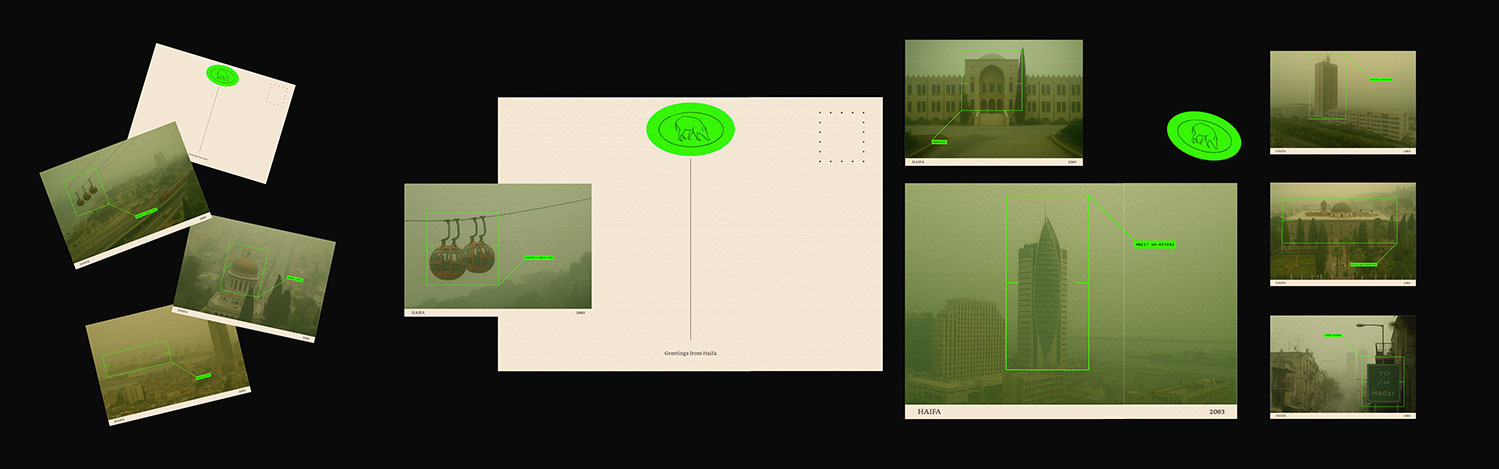
בפרויקט Haifa 2083 מציגה ליאת לזבר סדרת גלויות תיירותיות־אזהרתיות, המדמיינות את חיפה בשנת 2083 תחת ענן זיהום כבד. הדימויים, המבוססים על אתרים אייקוניים בעיר, מעניקים לפורמט הנוסטלגי של הגלויות פרשנות ביקורתית. זהו עיבוד מחודש לפרויקט משנה א׳, שנוצר בקורס "תפיסה חזותית" בהנחיית נסטיה פייביש, וכעת שודרג לאור ההתקדמות בבינה המלאכותית ותחושת הדחיפות סביב משבר האקלים. "כרגע, כתושבת חדשה של חיפה, רציתי לעורר שאלות על אחריות סביבתית והדחקה קולקטיבית," היא אומרת.
מה משך אותך לתחום?
מה שמשך אותי לתחום הוא קודם כול סקרנות. עד לפני ארבע שנים בכלל לא הכרתי את המונח "תקשורת חזותית", אבל כילדה ונערה כל עולמי היה יצירה – עיצוב, ציור, פיסול וכל עבודת קראפט אפשרית. בגיל 16 החלטתי שארצה לעסוק בעיצוב גרפי, אבל כששיתפתי את הרעיון עם המשפחה הסובייטית שלי (אמא, אני אוהבת אותך!), ההתלהבות לא הייתה בשיאה – אז הלכתי ללמוד ביולוגיה, כימיה ומדעי החברה.
בגיל 21 עברתי לתל־אביב, כמו הרבה נערות פריפריה, ושם נחשפתי לראשונה לעולם התקשורת החזותית. חזרתי הביתה עם ההבנה שזה מה שאני רוצה ללמוד, ולהפתעתי אמא שלי אמרה: "כל מה שתרצי – העיקר שתעשי כבר תואר". עם האמירה הזו, הרבה סקרנות וקצת ידע בתחום, ניגשתי למבחני הקבלה לוויצו – והשאר היסטוריה.
תני לנו ציטוט שיעורר בנו השראה.
״כשאת מקבלת את התשובה מתוכך, אף אחד לא יכול לבלבל אותך, את שם.״
לאן ניסית להתקבל ללימודים ולאן התקבלת?
בתקופה שבה ניסיתי להתקבל ללימודים גרתי בתל־אביב, אבל העיר הייתה עבורי כאוטית מדי. הגעגוע לצפון הלך והתחזק, עד שהפך לשיקול המרכזי בבחירה – ולכן ניגשתי למבחני קבלה רק בויצו. לשמחתי, הגעגוע ניצח.
איזה מרצה השפיע/ה עליך במיוחד?
נסטיה פייביש. הראשונה שהצליחה לגרום לי להרגיש שיש ערך למה שאני יוצרת. מלבד היותה מרצה מבריקה וחריפה, היא מעצבת גרפית וחוקרת חזותית ישראלית פוסט־סובייטית עם פרויקט מדהים בשם ״המהגרת״ שנוגע בנבכי הנפש שלי.
איזה מעצב/ת השפיע/ה עליך יותר מכל?
דן רייזינגר. יש באמת צורך להרחיב למה?
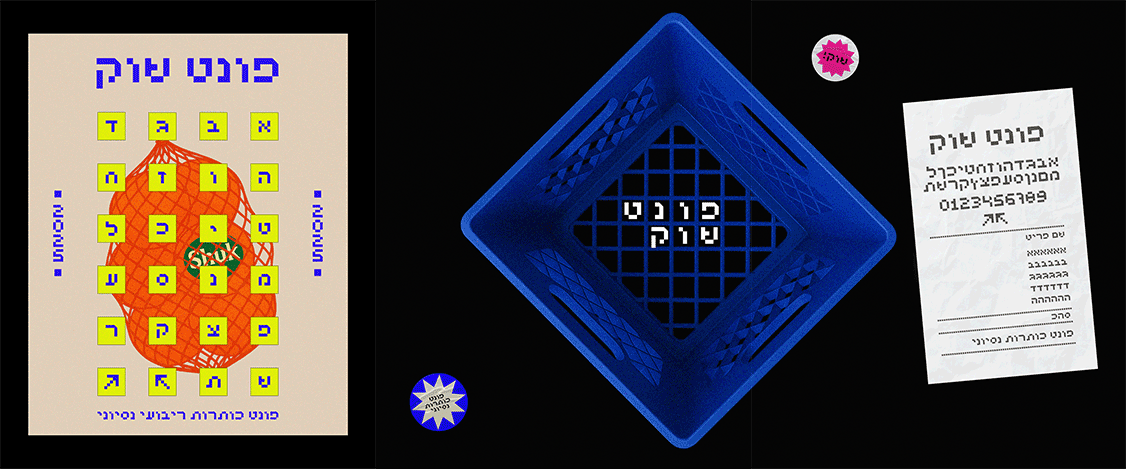
פונט שוק הוא פונט כותרות ריבועי־ניסיוני שיצרה ליאת לזבר במסגרת קורס מיתוג לתערוכת הבוגרים של המחלקה לתקשורת חזותית, 2025. נקודת המוצא שלה הייתה חיפוש אחר מקומות חיפאיים על־זמניים עם אופי מקומי מובהק, וההשראה המרכזית הגיעה משוק תלפיות האגדי – מרחב חזותי יומיומי, לא "מעוצב כמו שצריך", אך שופע אופי וחן מקומי. במהלך שיטוטיה בשוק, ליאת התבוננה בקבלות, שקי רשת, קופסאות פלסטיק ושלטים מאולתרים, וזיהתה מכנה משותף בולט – הצורניות הריבועית. מתוך הזיהוי הזה נולד הרצון לבנות פונט עצמאי, שנוצר בחיפוש אינטואיטיבי וללא ידע מוקדם בעיצוב פונטים. "התוצאה היא פונט גס וניסיוני, שלא מתיימר להיות מדויק, אבל בהחלט שמח בחלקו"ֿ, היא אומרת.
במה היית עוסקת אם לא היית מעצבת?
כנראה בתחום הטיפול ההוליסטי, שדרך אגב, עוד לא ויתרתי על החלום הזה.
איפה את רואה את עצמך בעוד חמש שנים מהיום?
יש לי תשובה קצת מעצבנת, אבל איפה שמדויק לי.
ספר פרוזה/עיון אחרון שקראת:
מה שלימד הבודהה - ואלפולה ראהולה
באיזה פונט את רוצה שיכתבו על המצבה שלך?
תכלס, מעדיפה שישרפו אותי וישתלו איזה עץ של פיקוס כינורי במקום, אבל אפשרי שיהיה שלט קטן בפונט נרקיסים.
יש לך המלצה מוזיקלית?
בשפע, ואני אנסה מאוד לא להתפזר, אבל בגדול: iogi או בשמו המלא יוגב גלוסמן – כל דבר שיוגי מוציא הוא פשוט זהב. האלבום ״שעות רגישות״ של אבישי כהן. כל שיר של תומר ישעיהו. ואחרון — ״שלוש תנועות״ של אביתר בנאי. וגם זה: youtube.com/watch?v=sv1KQjiMVkE
מה משמעות החיים?
לעבור שיעורים, לחמול, לדייק, לאהוב, להיות פגיעה ולהקשיב לאינטואיציה שלך.
מה שם החיבה שלך?
ליאתי, ואפילו אעדיף שיפנו אליי כך.
קיצור מקלדת אהוב?
Cmd+Z - מציל נפשות.
כתב/י בבקשה את המילה הבאה בכתב היד שלך: